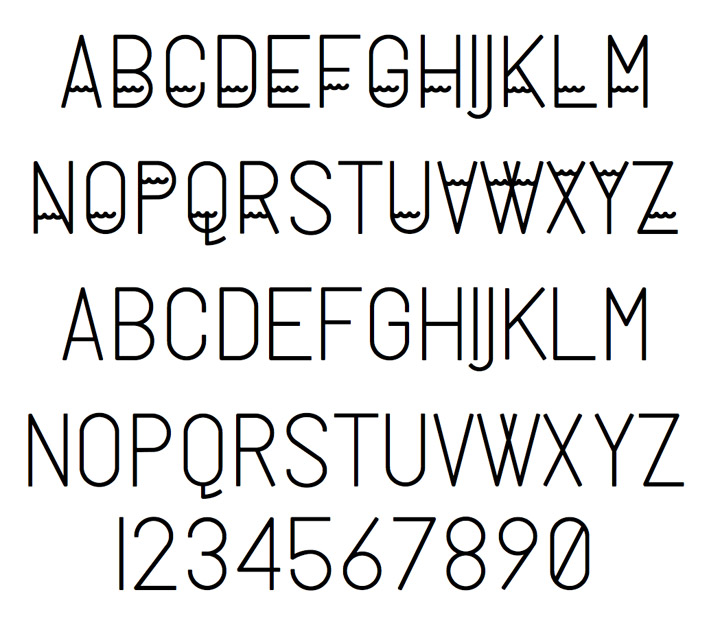
Una tipografía muy elegante y minimalista, basada en la gran ciudad de Milán y en los ríos que la recorren de punta a punta.
Marco Oggian es un diseñador e ilustrador nacido en Venecia y que actualmente vive en España. Ha sido reconocido numerosas veces por su trabajo en plataformas como Behance.
A very elegant and minimalist typography, based on the great city of Milan and the rivers that run from end to end.
Marco Oggian is a designer and illustrator born in Venice and currently living in Spain. He has been recognized numerous times for his work on platforms such as Behance.